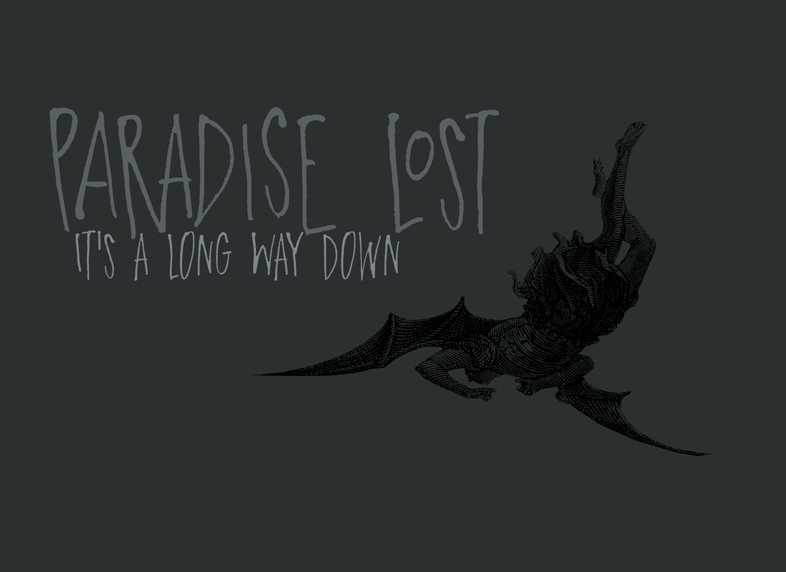
A fonte ‘DK Paradise Lost Font’ oferece um visual autêntico e envolvente que se adapta perfeitamente aos projetos manuscritos ou escrita à mão, criando texturas naturais e sutis. Desenvolvida pelo designer Hamilton, esta fonte é perfeita para quem busca uma mão-de-videira única e deslumbrante. Ideal tanto para trabalhos de arte gráfica como para projetos manuais, ‘DK Paradise Lost Font’ se destaca com sua qualidade impressionante de escrita à mão. Seu estilo singular permite que você personalize seus projetos com um toque distintivo que pode destacar em qualquer tipo de trabalho, desde livros de arte até cartões personalizados. Embora a fonte seja gratuita para uso pessoal, Hamilton oferece opções de licenciamento mais amplos, incluindo ajustes de espaçamento (kerning), direitos de embedder e acesso a todos os caracteres, inclusive o número 4. Essa fonte é perfeita para designers e artistas que buscam uma fonte autêntica e versátil sem se preocupar com as restrições comerciais ou restritivas. Não use esta fonte em jogos, aplicativos ou software sem a permissão adequada do designer. Se você precisa de um licenciamento para usá-la em projetos que exigem isso, Hamilton também oferece opções de compra direto através do seu site: hanodedfonts.com. Além disso, o arquivo ZIP incluído na sua compra contém uma explicação detalhada sobre os termos de uso da fonte e outras informações úteis. Portanto, ‘DK Paradise Lost Font’ é a escolha perfeita para quem procura uma fonte única que se destaca em seus trabalhos manuscritos, sem comprometer suas necessidades comerciais ou restritivas.